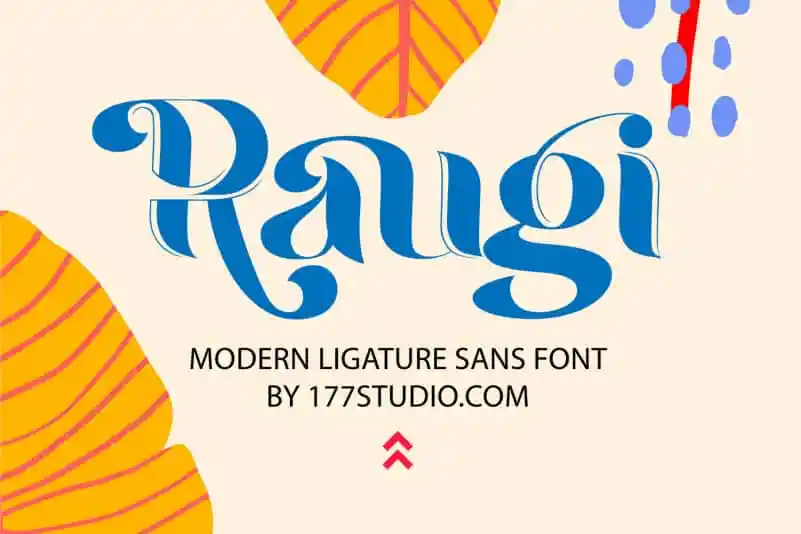
Raugi – Ligature Sans Serif Font – Download Grátis
Raugi Font é uma fonte de tipo sans-serif que oferece algo único e memorável à sua coleção. Ela tem contraste alto e incorpora estilos sofisticados, dando-lhe um toque moderno sem perder a elegância. Inspirada no estilo clássico de Caslon, Raugi Font reinterpreta este design em uma versão ligature que é adequada para uma ampla gama de aplicações. Seja para criar belos logos ou incríveis postagens do blog, as alternativas e ligaturas presentes na fonte trazem uma personalidade única a qualquer projeto. Raugi é perfeito para criar mensagens impactantes, como citações em eventos especiais como casamentos, bem como para tornar seu Instagram mais interessante. Seja onde estiver aplicada, Raugi garante um design arrojado e moderno que adicionará uma identidade visual inovadora a qualquer projeto impresso ou digital. Sua versatilidade faz dela uma escolha ótima tanto para iniciantes quanto para designers experientes em busca de algo novo na fontes ligature sans serif disponíveis no mercado.